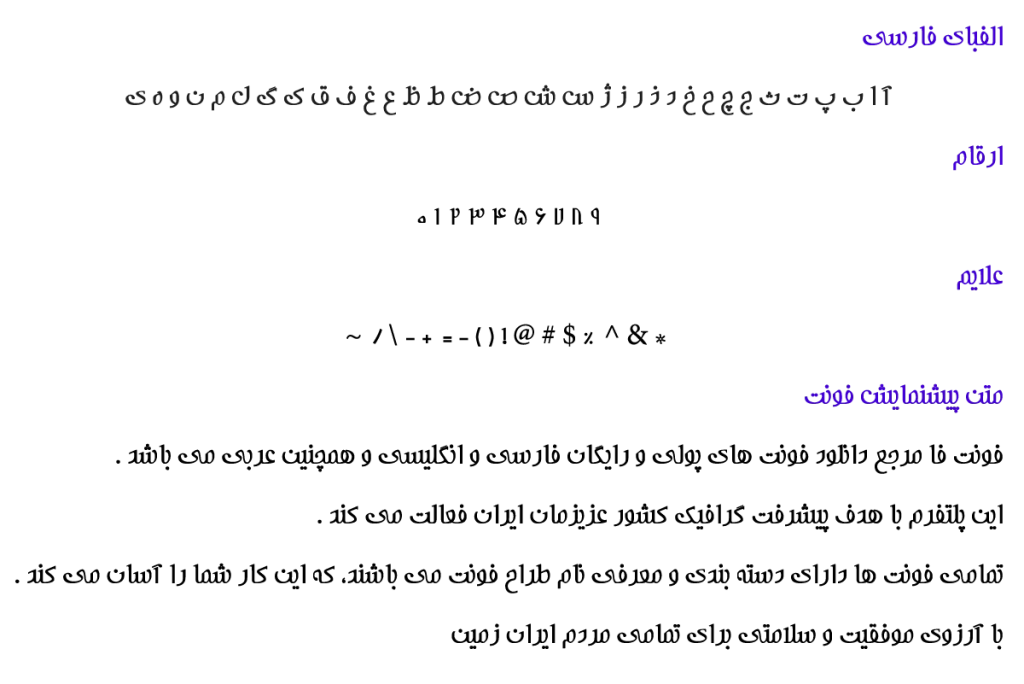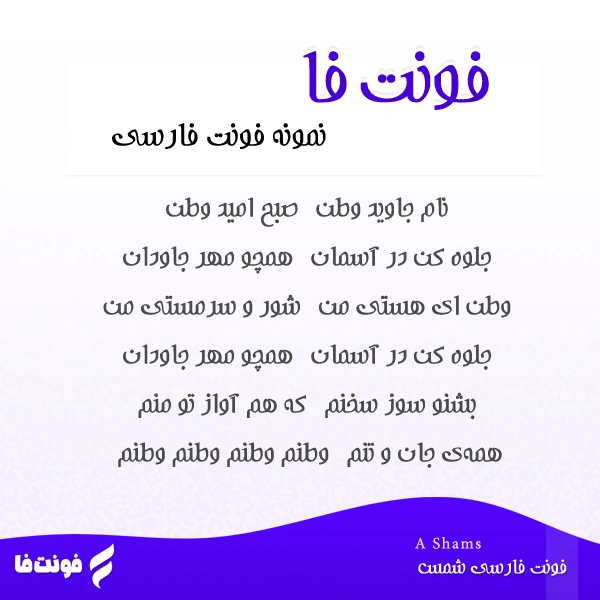
فونت فارسی شمس – A Shams
طراح فونت: محمدرضا شمس الکتابی نوع فونت: فونت فانتزی
توضیحات و معرفی فونت شمس
فونت فارسی شمس ( A Shams ) از مجموعه فونت های آزاد می باشد، و نیز نوع فونت فانتزی می باشد.
فونت خوشگل مربوط توسط محمدرضا شمس الکتابی در سال 1390 طراحی و ساخته شده است.
و نیز فونت A Shams در یک وزن معمولی است.
در عکس زیر میتوانید جلوهای از این تایپ فیس را در قالب شعر ایرانی ببینید.